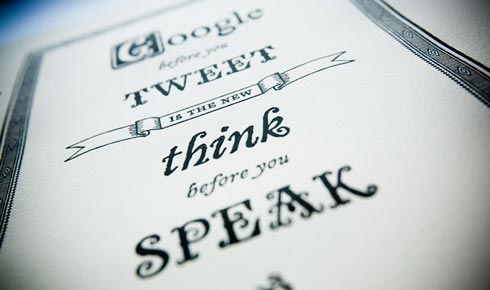
… ist das neue »Erst denken, dann sprechen«. Wer sich das nicht hinter die Ohren schreiben möchte, kann die neue Weisheit der Socials auch schwarz auf weiß bestellen. Entworfen von Joe Newton (@TheJoeNewton), mit der Schrift Olduvai, gedruckt auf 300 g Somerset-Velvet-Baumwollpapier im Buchdruck, Format A4 und erhältlich bei I love Typography für 15,00 Dollar.
Wundervoll old school.